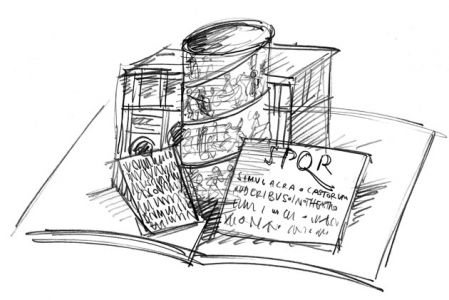
Typo Pop-Up Buch
Es kommt mir grad so in den Sinn: Hat jemand Lust, mit mir ein Typo-Pop-Up-Buch zu entwickeln?
Vielleicht so 4 bis 6 Doppelseiten zur Geschichte der Schrift/Typografie, oder eine Galerie der großen (Ent-) Würfe (Gutenberg, Garamond, Barock, Helvetica, Meta, Thesis o.ä.). Aber nicht illustrativ, Gutenberg an der Presse oder sowas, sondern nur "Buchstabenbilder".
Paper Engineering könnt' ich machen ...
Ein Pop-up-Buch ist eines, bei dem einem beim Aufklappen plastische Objekte, die zuvor durch kustvolle Faltung flach waren, entgegenkommen. Oft kann man durch ziehen einer Lasche o.ä. zusätzlich für Bewegung sorgen. In diesem Fall soll das Thema eben Typographie sein.
Hier noch ein Beispiel aus einem meiner Lieblingsbücher als Kind:
Pension zum ewigen Frieden (Haunted House) von Jan Pienkowski.
Hach… «Haunted House» auch eines meiner Lieblingsbücher als Kind. Erinnere mich an ein ca. A4-Format mit einer knallgrünen Türe drauf, no?
Auch ich habe es geliebt, tue es bis heute und freue mich schon, es meinem Sohnemann zeigen zu können!
Wie sähe das im Bereich Typografie aus?
Ausklappbare Serifen? Veränderbarer Zeilenabstand (ich erinnere mich an ein Sachbuch für Kinder über den Lebensraum "Wiese", wo so aus einer Puppe ein Schmetterling wird)?
Ich bin etwas ratlos was man da machen könnte...
Ihr glaubt gar nicht, wie mich das freut, dass es hier so viele Pop-Up-Freunde gibt. Ich selbst habe zwei (oder sind es schon drei) Regalmeter voll davon ...
Der englische Markt hat viele solcher Titel lieferbar, in DE muss man die mit der Lupe suchen. In der Regel schießt der Vertrieb (im Verlag) solche Titel schon frühzeitig ab, denn "die verkaufen sich nicht". Weil man glaubt, dass die Buchhändler sie nicht mögen (schnell zerfledderte Ansichtsexemplare). Doch eines der erfolgreichsten US-Kinderbücher ist zur Zeit "Alice in Wonderland", adaptiert von Robert Sabuda, einem Großmeister der Pop-Up-Kunst. Und es ist großartig. Wer mal reinschauen mag:
Schwebt Dir so etwas in dieser Richtung vor – dreidimensional natürlich?
– Wo bei ich denn Waidmann etwas dünn finde.
da müssen 3d-buchstaben aufpoppen!
als 2d untergrund könnte man ja dann ein einsatzgebiet der schrift
zeigen. aber ich habe von popup büchern keine ahnung, ich kenne
sowas kaum – hier im osten gabs eher diese schiebebücher.
ein bauernhof mit einer kuh, schweinen und kücken.
diese hatten papier streifen, die aus den hinterteilen herausschauten
und mit den tieren bzw. körperteilen der tiere verbunden waren.
die kuh konnte dann mit den kopf wackeln, die kücken konnten ein
paar cm vor und zurücklaufen und da schwein sprang auf und ab. ;)
… bzw. wie Norbert sagte: in England wächst man praktisch mit diesen Büchern auf. Nun dachte ich aber auch eher, es klappten einem richtige Buchstaben entgegen, zum Abtasten – und eben nicht die Trajanssäule, Gutenberg in der Werkstatt, Herr Johnson in der Londoner U-Bahn oder Adrian Frutiger, der durch den Pariser Flughafen stakst – wobei auch das spaßig werden könnte.
Ja, fürs Ungegenständliche brauche ich ja auch die Kollaboteure ...
Noch ein paar Vorschläge ...